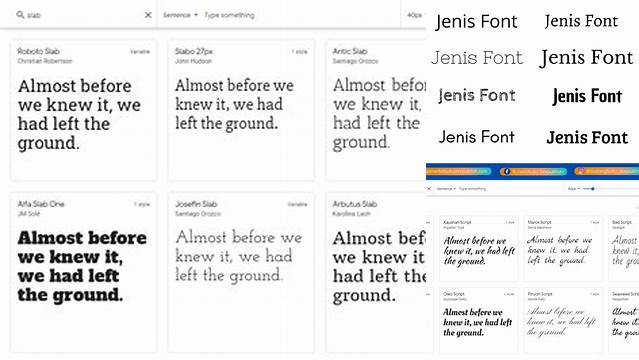
Font Cutting: Panduan Lengkap Untuk Desain Stiker Keren
Cutting sticker adalah salah satu cara kreatif untuk menghias berbagai media, mulai dari kendaraan hingga produk promosi. Pemilihan jenis font yang tepat adalah kunci untuk menghasilkan desain yang tidak hanya menarik secara visual, tetapi juga mudah dibaca dan sesuai dengan tujuan penggunaan. Dalam artikel ini, kita akan membahas secara mendalam tentang jenis font untuk cutting, mulai dari karakteristik yang ideal hingga tips memilih font yang paling cocok untuk proyek Anda. Mari kita mulai!
1. Memahami Karakteristik Font yang Ideal untuk Cutting Sticker
Guys, sebelum kita memilih font, penting banget nih buat memahami karakteristik font yang ideal untuk cutting sticker. Gak semua font cocok, lho! Beberapa hal krusial yang perlu diperhatikan adalah ketebalan garis, detail, dan keterbacaan. Yuk, kita bedah satu per satu!
- Ketebalan Garis: Font yang digunakan untuk cutting sticker sebaiknya memiliki ketebalan garis yang konsisten dan cukup tebal. Font dengan garis terlalu tipis akan sulit dipotong oleh mesin cutting dan berisiko putus atau rusak. Idealnya, pilih font dengan ketebalan garis yang cukup untuk memastikan hasil cutting yang presisi.
- Detail yang Sederhana: Hindari font dengan detail yang terlalu rumit atau banyak lekukan. Font semacam ini akan menyulitkan proses cutting dan berpotensi menghasilkan hasil yang kurang rapi. Pilihlah font dengan desain yang simpel dan mudah dikenali, bahkan dalam ukuran kecil.
- Keterbacaan: Keterbacaan adalah faktor utama yang harus dipertimbangkan. Pastikan font yang dipilih mudah dibaca, baik dari jarak dekat maupun jauh. Font yang terlalu artistik atau memiliki bentuk yang unik mungkin terlihat menarik, tetapi bisa jadi sulit dibaca.
- Jenis Font yang Direkomendasikan: Beberapa jenis font yang sangat direkomendasikan untuk cutting sticker adalah font sans-serif, seperti Arial, Helvetica, dan Futura. Font-font ini memiliki bentuk yang bersih, sederhana, dan mudah dipotong. Font serif, seperti Times New Roman, juga bisa digunakan, tetapi perlu diperhatikan ketebalan garis dan detailnya.
Dengan memahami karakteristik ini, Anda akan lebih mudah memilih font yang tepat untuk menghasilkan cutting sticker yang berkualitas.
2. Jenis Font Sans-Serif Terbaik untuk Cutting Sticker
Font sans-serif, atau font tanpa kait, adalah pilihan yang sangat populer dan sering digunakan untuk cutting sticker. Keunggulan utama dari font jenis ini adalah desainnya yang bersih, modern, dan mudah dibaca. Berikut ini beberapa jenis font sans-serif terbaik yang bisa Anda pertimbangkan:
- Arial: Font klasik yang sangat serbaguna. Arial memiliki bentuk yang sederhana, mudah dibaca, dan tersedia dalam berbagai variasi ketebalan. Cocok untuk berbagai keperluan, mulai dari teks singkat hingga judul.
- Helvetica: Font legendaris yang dikenal dengan kejelasan dan kesederhanaannya. Helvetica sangat cocok untuk desain yang membutuhkan tampilan profesional dan modern. Namun, perlu diperhatikan bahwa beberapa variasi Helvetica mungkin memiliki garis yang terlalu tipis untuk cutting sticker.
- Futura: Font geometris yang memiliki tampilan futuristik dan elegan. Futura sangat cocok untuk desain yang ingin tampil beda dan menarik perhatian. Perhatikan ketebalan garisnya agar hasil cutting tetap optimal.
- Roboto: Font yang dikembangkan oleh Google dan sangat populer di kalangan desainer. Roboto memiliki tampilan yang modern, mudah dibaca, dan cocok untuk berbagai aplikasi.
- Open Sans: Font yang dirancang untuk keterbacaan yang optimal di layar. Open Sans memiliki bentuk yang ramah dan mudah dibaca, bahkan dalam ukuran kecil. Cocok untuk desain yang membutuhkan keterbacaan tinggi.
Dengan memilih salah satu dari font sans-serif di atas, Anda sudah selangkah lebih dekat untuk menghasilkan cutting sticker yang berkualitas.
3. Jenis Font Serif yang Cocok untuk Cutting Sticker
Meskipun font sans-serif lebih populer, jenis font serif juga bisa digunakan untuk cutting sticker, asalkan dipilih dengan bijak. Font serif, atau font berkait, memiliki ciri khas berupa adanya tambahan garis kecil di ujung huruf. Berikut ini beberapa pilihan font serif yang cocok:
- Times New Roman: Font klasik yang memiliki tampilan formal dan elegan. Times New Roman bisa digunakan, tetapi perlu diperhatikan ketebalan garisnya agar tidak terlalu tipis saat dipotong.
- Georgia: Font yang dirancang untuk keterbacaan di layar. Georgia memiliki bentuk yang lebih tebal dan mudah dibaca dibandingkan Times New Roman, sehingga lebih cocok untuk cutting sticker.
- Playfair Display: Font serif yang memiliki tampilan modern dan elegan. Playfair Display cocok untuk desain yang membutuhkan sentuhan artistik.
- Lora: Font serif yang memiliki tampilan yang hangat dan bersahabat. Lora cocok untuk desain yang ingin menampilkan kesan ramah dan mudah didekati.
Saat menggunakan font serif, pastikan untuk memilih variasi dengan ketebalan garis yang cukup dan hindari detail yang terlalu rumit. Hal ini akan memastikan hasil cutting yang optimal dan mudah dibaca.
4. Font Tebal vs. Tipis: Mana yang Lebih Baik untuk Cutting Sticker?
Pertanyaan ini sering muncul nih, guys! Jawabannya adalah, tergantung pada desain dan tujuan Anda. Font tebal umumnya lebih mudah dipotong dan lebih terlihat jelas, terutama pada ukuran yang lebih kecil. Font tipis, di sisi lain, dapat memberikan kesan yang lebih elegan dan modern, tetapi berisiko sulit dipotong dan kurang terbaca.
- Font Tebal: Keunggulan utama font tebal adalah keterbacaannya yang tinggi. Font tebal sangat cocok untuk teks yang perlu terlihat jelas dari jarak jauh, seperti pada stiker mobil atau spanduk. Selain itu, font tebal lebih mudah dipotong karena memiliki garis yang lebih tebal, sehingga mengurangi risiko putus atau rusak.
- Font Tipis: Font tipis dapat memberikan kesan yang lebih elegan dan modern. Font tipis cocok untuk desain yang membutuhkan tampilan yang lebih halus dan minimalis. Namun, perlu diingat bahwa font tipis lebih sulit dipotong, terutama pada ukuran yang kecil. Pastikan untuk memilih font tipis dengan ketebalan garis yang cukup dan menghindari detail yang terlalu rumit.
- Pilihan Terbaik: Pilihan terbaik adalah memilih font dengan ketebalan garis yang seimbang. Font yang tidak terlalu tebal dan tidak terlalu tipis, sehingga mudah dipotong dan tetap terbaca. Pertimbangkan juga ukuran stiker dan jarak pandang saat memilih ketebalan font.
5. Tips Memilih Font yang Tepat untuk Cutting Sticker Mobil
Cutting sticker mobil membutuhkan perhatian khusus dalam pemilihan font, guys. Karena stiker akan terpapar cuaca dan dilihat dari berbagai sudut pandang, beberapa tips berikut ini akan sangat membantu:
- Keterbacaan Jarak Jauh: Pilih font yang mudah dibaca dari jarak jauh. Hindari font yang terlalu artistik atau memiliki detail yang rumit, karena akan sulit dikenali saat mobil melaju.
- Ketahanan Terhadap Cuaca: Pertimbangkan ketahanan font terhadap cuaca. Font yang terlalu tipis atau memiliki detail yang terlalu rumit berisiko rusak atau pudar akibat paparan sinar matahari dan hujan.
- Ukuran yang Tepat: Sesuaikan ukuran font dengan ukuran mobil dan area yang akan ditempel stiker. Font yang terlalu kecil akan sulit dibaca, sedangkan font yang terlalu besar akan terlihat berlebihan.
- Warna yang Kontras: Pilih warna font yang kontras dengan warna mobil. Hal ini akan memastikan teks terlihat jelas dan mudah dibaca.
- Gaya yang Sesuai: Pilih gaya font yang sesuai dengan gaya mobil dan kepribadian pemilik. Font yang tepat akan membuat tampilan mobil semakin menarik dan personal.
6. Font untuk Cutting Sticker Motor yang Stylish
Motor juga menjadi sasaran populer untuk cutting sticker, guys! Untuk cutting sticker motor, ada beberapa tips khusus yang perlu diperhatikan:
- Ukuran yang Proporsional: Sesuaikan ukuran font dengan ukuran motor dan area yang akan ditempel stiker. Font yang terlalu besar akan terlihat berlebihan, sedangkan font yang terlalu kecil akan sulit dibaca.
- Desain yang Dinamis: Pilih font yang memiliki desain dinamis dan sesuai dengan karakter motor. Font dengan sudut tajam atau garis yang tegas akan memberikan kesan sporty dan agresif.
- Ketahanan Terhadap Getaran: Pertimbangkan ketahanan font terhadap getaran. Font yang terlalu tipis atau memiliki detail yang terlalu rumit berisiko rusak akibat getaran motor.
- Pilihan Warna yang Tepat: Pilih warna font yang sesuai dengan warna motor dan selera pribadi. Kombinasi warna yang tepat akan membuat tampilan motor semakin menarik.
- Penempatan yang Strategis: Pertimbangkan penempatan stiker pada motor. Letakkan stiker pada area yang mudah terlihat dan tidak mengganggu fungsi motor.
7. Font yang Ideal untuk Cutting Sticker Kaca
Cutting sticker kaca membutuhkan perhatian khusus karena kaca memiliki permukaan yang licin dan transparan. Berikut adalah beberapa tips memilih font yang ideal:
- Ketebalan yang Cukup: Pilih font dengan ketebalan yang cukup agar terlihat jelas pada kaca. Font yang terlalu tipis akan sulit dilihat, terutama jika terkena pantulan cahaya.
- Keterbacaan Terhadap Cahaya: Pertimbangkan keterbacaan font terhadap cahaya. Hindari font yang memiliki detail yang terlalu rumit atau terlalu banyak lekukan, karena akan sulit dibaca saat terkena cahaya matahari.
- Warna yang Kontras: Pilih warna font yang kontras dengan warna latar belakang. Warna putih atau terang biasanya menjadi pilihan yang baik untuk cutting sticker kaca.
- Jenis Font yang Sederhana: Pilih jenis font yang sederhana dan mudah dibaca. Font sans-serif adalah pilihan yang sangat baik untuk cutting sticker kaca.
- Ukuran yang Proporsional: Sesuaikan ukuran font dengan ukuran kaca dan area yang akan ditempel stiker. Font yang terlalu kecil akan sulit dibaca, sedangkan font yang terlalu besar akan terlihat berlebihan.
8. Font Keren untuk Cutting Sticker Nama dan Kata-Kata
Cutting sticker nama dan kata-kata adalah cara yang populer untuk mengekspresikan diri atau memberikan sentuhan personal pada barang-barang. Berikut adalah beberapa font keren yang bisa Anda gunakan:
- Script Fonts: Font script atau font tulisan tangan dapat memberikan kesan yang elegan dan personal. Font jenis ini cocok untuk nama, kutipan inspiratif, atau kata-kata yang ingin ditonjolkan.
- Bold Fonts: Font tebal memberikan kesan yang kuat dan berani. Font jenis ini cocok untuk nama atau kata-kata yang ingin menarik perhatian.
- Unique Fonts: Font unik dengan desain yang kreatif dan menarik dapat memberikan kesan yang berbeda dan personal. Pilihlah font yang sesuai dengan kepribadian Anda atau tema yang ingin ditampilkan.
- Simple Fonts: Font sederhana dengan desain yang bersih dan mudah dibaca dapat memberikan kesan yang modern dan minimalis. Font jenis ini cocok untuk nama atau kata-kata yang ingin tampil elegan.
9. Font yang Mudah Dipotong untuk Cutting Sticker Custom
Saat membuat cutting sticker custom, pemilihan font yang mudah dipotong sangat penting. Berikut adalah beberapa tips untuk memilih font yang tepat:
- Hindari Font yang Rumit: Hindari font yang memiliki detail yang terlalu rumit atau banyak lekukan. Font semacam ini akan menyulitkan proses cutting dan berpotensi menghasilkan hasil yang kurang rapi.
- Pilih Font yang Tebal: Pilih font dengan ketebalan garis yang cukup. Font yang terlalu tipis akan sulit dipotong dan berisiko putus atau rusak.
- Perhatikan Detail Huruf: Perhatikan detail huruf, seperti ujung huruf yang tajam atau sudut yang kecil. Hindari detail yang terlalu kecil atau rumit, karena akan sulit dipotong.
- Uji Coba: Sebelum memotong cutting sticker dalam jumlah banyak, lakukan uji coba dengan memotong beberapa sampel. Hal ini akan membantu Anda memastikan bahwa font yang dipilih mudah dipotong dan menghasilkan hasil yang optimal.
10. Font Gratis Terbaik untuk Cutting Sticker: Pilihan Hemat Biaya
Siapa bilang harus bayar mahal untuk font yang bagus? Ada banyak font gratis terbaik yang bisa Anda gunakan untuk cutting sticker. Berikut adalah beberapa sumber dan pilihan yang bisa Anda coba:
- Google Fonts: Google Fonts adalah sumber font gratis yang sangat populer dan menyediakan ribuan font berkualitas tinggi. Font-font di Google Fonts dapat diunduh dan digunakan secara gratis untuk keperluan pribadi maupun komersial.
- DaFont: DaFont adalah situs web yang menyediakan berbagai macam font gratis dari berbagai kategori. Anda dapat menemukan font yang unik dan menarik di situs web ini.
- Font Squirrel: Font Squirrel adalah situs web yang menyediakan font gratis berkualitas tinggi yang telah dipilih secara cermat. Font-font di Font Squirrel seringkali memiliki lisensi yang memungkinkan penggunaan komersial.
- Behance: Behance adalah platform tempat desainer dari seluruh dunia berbagi karya mereka. Anda dapat menemukan font gratis yang menarik di platform ini.
11. Font untuk Cutting Sticker yang Mudah Dibaca dalam Ukuran Kecil
Saat membuat cutting sticker dengan ukuran kecil, keterbacaan menjadi faktor yang sangat penting. Berikut adalah beberapa tips untuk memilih font yang mudah dibaca dalam ukuran kecil:
- Pilih Font Sans-Serif: Font sans-serif cenderung lebih mudah dibaca dalam ukuran kecil dibandingkan font serif. Bentuknya yang sederhana dan bersih membuat huruf lebih mudah dikenali.
- Perhatikan Ketebalan Garis: Pilih font dengan ketebalan garis yang cukup. Font yang terlalu tipis akan sulit dibaca, terutama dalam ukuran kecil.
- Hindari Font yang Rumit: Hindari font yang memiliki detail yang terlalu rumit atau banyak lekukan. Detail yang rumit akan sulit dikenali dalam ukuran kecil.
- Uji Coba: Sebelum memotong cutting sticker dalam jumlah banyak, lakukan uji coba dengan memotong beberapa sampel. Hal ini akan membantu Anda memastikan bahwa font yang dipilih mudah dibaca dalam ukuran kecil.
12. Jenis Font yang Cocok untuk Cutting Sticker Vinyl
Vinyl adalah bahan yang umum digunakan untuk cutting sticker. Beberapa jenis font lebih cocok untuk bahan ini daripada yang lain. Berikut adalah beberapa tips:
- Ketebalan yang Cukup: Pilih font dengan ketebalan garis yang cukup agar mudah dipotong oleh mesin cutting vinyl.
- Detail yang Sederhana: Hindari font dengan detail yang terlalu rumit atau banyak lekukan, karena akan menyulitkan proses cutting dan berpotensi menghasilkan hasil yang kurang rapi.
- Keterbacaan: Pastikan font yang dipilih mudah dibaca, baik dari jarak dekat maupun jauh. Pertimbangkan ukuran stiker dan jarak pandang saat memilih font.
- Kesesuaian dengan Warna Vinyl: Pilih font yang memiliki warna yang kontras dengan warna vinyl. Hal ini akan memastikan teks terlihat jelas dan mudah dibaca.
13. Mengapa Keterbacaan Font Penting untuk Cutting Sticker?
Keterbacaan adalah kunci utama dalam desain cutting sticker. Jika font tidak mudah dibaca, pesan yang ingin disampaikan akan sulit diterima oleh orang lain. Berikut adalah beberapa alasan mengapa keterbacaan font sangat penting:
- Efektivitas Komunikasi: Cutting sticker digunakan untuk menyampaikan pesan atau informasi. Jika font tidak mudah dibaca, pesan tersebut tidak akan tersampaikan dengan efektif.
- Pengenalan Merek: Cutting sticker sering digunakan untuk menampilkan merek atau logo. Jika font sulit dibaca, orang akan kesulitan mengenali merek Anda.
- Daya Tarik Visual: Font yang mudah dibaca akan membuat cutting sticker terlihat lebih menarik dan profesional.
- Kepuasan Pelanggan: Cutting sticker yang mudah dibaca akan memberikan pengalaman yang lebih baik bagi pelanggan.
14. Font yang Sering Digunakan dalam Cutting Sticker untuk Bisnis
Untuk keperluan bisnis, pemilihan font yang tepat sangat penting untuk membangun citra merek yang kuat. Berikut adalah beberapa font yang sering digunakan dalam cutting sticker untuk bisnis:
- Arial: Font klasik yang serbaguna dan mudah dibaca. Cocok untuk berbagai keperluan bisnis, mulai dari logo hingga informasi kontak.
- Helvetica: Font yang profesional dan modern. Cocok untuk bisnis yang ingin menampilkan citra yang elegan dan berkelas.
- Roboto: Font yang modern dan mudah dibaca. Cocok untuk bisnis yang ingin menampilkan citra yang ramah dan mudah didekati.
- Futura: Font yang unik dan menarik perhatian. Cocok untuk bisnis yang ingin tampil beda dan kreatif.
15. Bagaimana Memilih Font yang Tepat untuk Cutting Sticker Toko?
Pemilihan font untuk cutting sticker toko harus disesuaikan dengan jenis bisnis dan target pasar. Berikut adalah beberapa tips:
- Sesuaikan dengan Jenis Bisnis: Pilih font yang sesuai dengan jenis bisnis Anda. Misalnya, untuk toko pakaian, Anda bisa menggunakan font yang elegan dan stylish, sedangkan untuk toko mainan, Anda bisa menggunakan font yang ceria dan menyenangkan.
- Pertimbangkan Target Pasar: Pilih font yang sesuai dengan target pasar Anda. Jika target pasar Anda adalah anak-anak, Anda bisa menggunakan font yang berwarna-warni dan lucu.
- Keterbacaan: Pastikan font mudah dibaca, baik dari jarak dekat maupun jauh. Pertimbangkan ukuran toko dan lokasi stiker.
- Konsistensi Merek: Gunakan font yang konsisten dengan merek Anda. Hal ini akan membantu membangun citra merek yang kuat.
16. Font untuk Cutting Sticker yang Cocok untuk Tema Vintage
Tema vintage atau retro memiliki daya tarik tersendiri. Untuk cutting sticker dengan tema ini, pemilihan font yang tepat sangat penting. Berikut adalah beberapa tips:
- Font Serif Klasik: Gunakan font serif klasik seperti Times New Roman atau Garamond untuk memberikan kesan vintage yang kuat.
- Font Script: Font script atau tulisan tangan dapat memberikan kesan yang elegan dan klasik. Pilihlah font script yang memiliki gaya yang sesuai dengan tema vintage.
- Font Display: Font display dengan desain yang unik dan menarik dapat memberikan kesan vintage yang khas. Pilihlah font display yang terinspirasi dari desain era klasik.
- Kombinasi Font: Kombinasikan beberapa jenis font untuk menciptakan tampilan yang unik dan menarik. Misalnya, Anda bisa menggunakan font serif untuk judul dan font script untuk subjudul.
17. Font yang Mudah Dibuat Outline untuk Cutting Sticker
Beberapa font lebih mudah dibuat outline daripada yang lain. Outline adalah garis luar yang mengelilingi huruf, yang berguna untuk memperjelas tampilan huruf pada cutting sticker. Berikut adalah beberapa tips:
- Pilih Font Tebal: Font tebal cenderung lebih mudah dibuat outline karena memiliki garis yang lebih jelas.
- Hindari Font yang Rumit: Font yang rumit dengan banyak detail akan menyulitkan proses pembuatan outline.
- Perhatikan Jarak Antar Huruf: Jarak antar huruf yang terlalu rapat dapat menyulitkan proses pembuatan outline. Pastikan ada jarak yang cukup antara huruf.
- Gunakan Software Desain: Gunakan software desain yang memiliki fitur pembuatan outline yang mudah digunakan. Software desain seperti Adobe Illustrator atau CorelDRAW adalah pilihan yang baik.
18. Font yang Direkomendasikan untuk Cutting Sticker Mobil Sport
Mobil sport membutuhkan cutting sticker dengan desain yang dinamis dan sporty. Berikut adalah beberapa font yang direkomendasikan:
- Font Bold Sans-Serif: Font bold sans-serif memberikan kesan yang kuat dan modern. Cocok untuk menampilkan nama merek atau informasi penting lainnya.
- Font dengan Sudut Tajam: Font dengan sudut tajam atau garis yang tegas memberikan kesan sporty dan agresif.
- Font yang Terinspirasi dari Balap: Font yang terinspirasi dari dunia balap, seperti font yang digunakan pada mobil balap, dapat memberikan kesan yang khas dan menarik.
- Font Italic: Font italic dapat memberikan kesan yang dinamis dan bergerak. Cocok untuk menampilkan nama merek atau logo.
19. Font yang Pas untuk Cutting Sticker di Jendela Mobil
Cutting sticker di jendela mobil memiliki tantangan tersendiri karena harus terlihat jelas dari dalam dan luar mobil. Berikut adalah beberapa tips:
- Warna yang Kontras: Pilih warna font yang kontras dengan warna kaca dan latar belakang. Warna putih atau terang biasanya menjadi pilihan yang baik.
- Ukuran yang Cukup Besar: Pastikan ukuran font cukup besar agar mudah dibaca dari dalam dan luar mobil.
- Jenis Font yang Sederhana: Pilih jenis font yang sederhana dan mudah dibaca. Font sans-serif adalah pilihan yang sangat baik.
- Hindari Detail yang Berlebihan: Hindari detail yang berlebihan pada font karena akan sulit dilihat dari jarak jauh.
20. Font untuk Cutting Sticker yang Tahan Lama dan Awet
Ketahanan dan keawetan cutting sticker sangat penting. Pemilihan font yang tepat juga berperan dalam hal ini. Berikut adalah beberapa tips:
- Pilih Font dengan Ketebalan yang Cukup: Font dengan ketebalan yang cukup akan lebih tahan lama karena tidak mudah pudar atau rusak.
- Hindari Font yang Terlalu Tipis: Font yang terlalu tipis lebih rentan terhadap kerusakan akibat gesekan atau paparan cuaca.
- Gunakan Bahan Cutting Sticker Berkualitas: Selain font, bahan cutting sticker juga berperan penting dalam ketahanan dan keawetan. Pilihlah bahan berkualitas tinggi yang tahan terhadap cuaca dan gesekan.
- Perawatan yang Tepat: Lakukan perawatan yang tepat pada cutting sticker, seperti membersihkannya secara berkala dan menghindari paparan langsung sinar matahari.
21. Jenis Font yang Sering Digunakan untuk Cutting Sticker Promosi
Cutting sticker promosi membutuhkan font yang menarik perhatian dan mudah diingat. Berikut adalah beberapa jenis font yang sering digunakan:
- Font Bold: Font tebal menarik perhatian dan mudah dibaca dari jarak jauh.
- Font yang Unik: Font yang unik dan kreatif akan membuat cutting sticker promosi Anda lebih menonjol.
- Font yang Sesuai dengan Tema: Pilih font yang sesuai dengan tema promosi Anda. Misalnya, untuk promosi makanan, Anda bisa menggunakan font yang ceria dan menyenangkan.
- Font yang Mudah Dibaca: Pastikan font mudah dibaca agar pesan promosi Anda tersampaikan dengan efektif.
22. Panduan Lengkap Memilih Font Cutting Sticker yang Sesuai Budget
Memilih font yang sesuai dengan budget adalah hal penting. Berikut adalah beberapa tips:
- Manfaatkan Font Gratis: Gunakan font gratis dari Google Fonts atau sumber lainnya untuk menghemat biaya.
- Pertimbangkan Lisensi: Perhatikan lisensi font sebelum menggunakannya. Pastikan Anda memiliki lisensi yang tepat untuk penggunaan komersial jika diperlukan.
- Pertimbangkan Jumlah Font: Gunakan font yang sederhana dan mudah dikombinasikan agar tidak perlu membeli banyak font.
- Ukur Kebutuhan: Ukur kebutuhan font Anda dengan cermat agar tidak membeli font yang tidak diperlukan.
23. Tips Menggabungkan Beberapa Jenis Font untuk Cutting Sticker yang Menarik
Menggabungkan beberapa jenis font dapat menciptakan tampilan yang menarik dan dinamis. Berikut adalah beberapa tips:
- Pilih Font yang Kontras: Pilih font yang memiliki kontras yang jelas, baik dalam bentuk maupun gaya. Misalnya, kombinasikan font sans-serif dengan font serif.
- Gunakan Hierarki Visual: Gunakan hierarki visual untuk memandu mata pembaca. Gunakan font yang lebih besar untuk judul dan font yang lebih kecil untuk subjudul atau deskripsi.
- Batasi Jumlah Font: Hindari menggunakan terlalu banyak jenis font. Idealnya, gunakan maksimal dua atau tiga jenis font dalam satu desain.
- Konsistensi: Pastikan ada konsistensi dalam penggunaan font. Gunakan font yang sama untuk elemen yang serupa, seperti judul atau subjudul.
24. Font Cutting Sticker yang Mudah Diwarnai dan Dikombinasikan Warna
Kemudahan pewarnaan dan kombinasi warna adalah pertimbangan penting. Berikut adalah beberapa tips:
- Pilih Font yang Tidak Terlalu Rumit: Font yang tidak terlalu rumit akan lebih mudah diwarnai dan dikombinasikan warna.
- Gunakan Warna yang Kontras: Pilih warna yang kontras agar teks terlihat jelas.
- Pertimbangkan Latar Belakang: Pertimbangkan warna latar belakang saat memilih warna font.
- Uji Coba: Lakukan uji coba pewarnaan dan kombinasi warna sebelum memproduksi cutting sticker dalam jumlah banyak.
25. Mengatasi Kesulitan dalam Memotong Font Rumit untuk Cutting Sticker
Font rumit memang menantang untuk dipotong. Berikut adalah beberapa tips untuk mengatasinya:
- Gunakan Mesin Cutting yang Presisi: Gunakan mesin cutting yang memiliki presisi tinggi untuk hasil yang lebih baik.
- Kurangi Ukuran: Coba kurangi ukuran font untuk mempermudah proses pemotongan.
- Perhatikan Pengaturan Mesin: Pastikan pengaturan mesin cutting sudah tepat, termasuk tekanan pisau dan kecepatan potong.
- Lakukan Uji Coba: Lakukan uji coba pemotongan pada bahan yang sama sebelum memproduksi cutting sticker dalam jumlah banyak.
26. Rekomendasi Software Desain untuk Memilih dan Mengedit Font Cutting Sticker
Software desain sangat membantu dalam memilih dan mengedit font. Berikut adalah beberapa rekomendasi:
- Adobe Illustrator: Software profesional dengan fitur lengkap untuk desain grafis.
- CorelDRAW: Software populer dengan antarmuka yang mudah digunakan.
- Canva: Software berbasis web yang mudah digunakan, terutama bagi pemula.
- Inkscape: Software gratis dan open source yang memiliki banyak fitur desain.
27. Bagaimana Memastikan Hasil Cutting Sticker dengan Font yang Sempurna?
Untuk memastikan hasil cutting sticker sempurna, perhatikan beberapa hal berikut:
- Kualitas Bahan: Gunakan bahan cutting sticker berkualitas tinggi.
- Pengaturan Mesin: Pastikan pengaturan mesin cutting sudah tepat.
- Desain yang Tepat: Pilih font yang mudah dipotong dan desain yang sederhana.
- Uji Coba: Lakukan uji coba sebelum memproduksi dalam jumlah banyak.
28. Peran Font dalam Membangun Identitas Merek Melalui Cutting Sticker
Font memainkan peran penting dalam membangun identitas merek. Berikut adalah beberapa hal yang perlu diperhatikan:
- Konsistensi: Gunakan font yang konsisten dengan merek Anda.
- Kepribadian Merek: Pilih font yang mencerminkan kepribadian merek Anda.
- Daya Ingat: Pilih font yang mudah diingat dan dikenali.
29. Tips Merawat dan Membersihkan Cutting Sticker dengan Berbagai Jenis Font
Perawatan yang tepat akan memperpanjang umur cutting sticker. Berikut adalah beberapa tips:
- Hindari Gesekan: Hindari gesekan yang berlebihan pada cutting sticker.
- Bersihkan dengan Lembut: Bersihkan cutting sticker dengan lembut menggunakan air sabun dan kain lembut.
- Hindari Bahan Kimia: Hindari penggunaan bahan kimia yang keras.
- Jaga dari Sinar Matahari Langsung: Hindari paparan sinar matahari langsung dalam jangka waktu lama.
30. Tren Font Terbaru untuk Cutting Sticker: Apa yang Sedang Populer?
Tren font terus berubah, guys! Untuk tetap up-to-date, berikut adalah beberapa tren font terbaru untuk cutting sticker:
- Font Modern Sans-Serif: Font sans-serif dengan desain yang modern dan minimalis masih menjadi favorit.
- Font Bold dan Tebal: Font bold dan tebal untuk menarik perhatian.
- Font dengan Sentuhan Retro: Font dengan sentuhan retro atau vintage untuk kesan klasik.
- Font yang Dipersonalisasi: Font yang dipersonalisasi dengan sentuhan unik dan kreatif.
Dengan panduan ini, semoga kalian semakin mahir dalam memilih jenis font untuk cutting dan menghasilkan desain yang memukau! Jangan ragu untuk bereksperimen dan menemukan font yang paling cocok dengan kebutuhan kalian, ya!